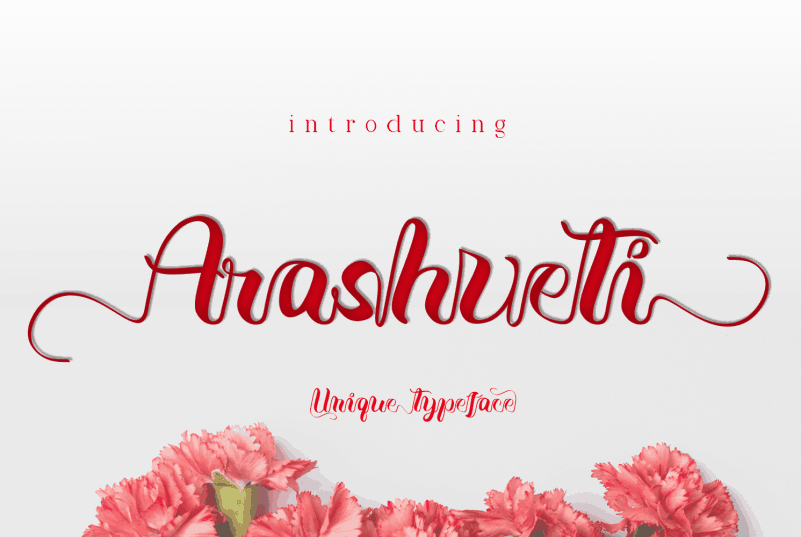
Arashveti Calligraphy Font – Download Grátis
A Arashveti Calligraphy Font é uma deliciosa tipografia escrita à mão inspirada no script javanês da Indonésia. Ela captura a elegância e a delicadeza do estilo de calligrafia ao desenhar um texto que se tornou um verdadeiro favorito. Esta fonte mantém o charme dos estilos tradicionais, incorporando novas técnicas para dar uma aparência jovem e fresca. É perfeita para aqueles que buscam um toque de elegância em sua tipografia, enquanto preservam a modernidade e frescor necessários. Se você busca uma fonte que seja ao mesmo tempo clássica e atual, então Arashveti é o escolha certa.